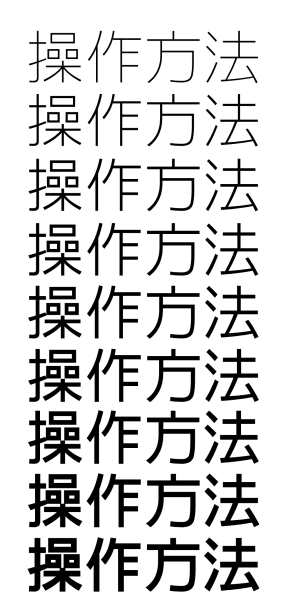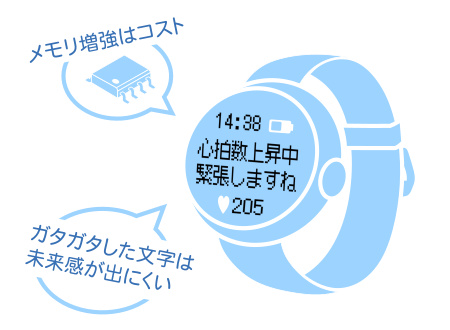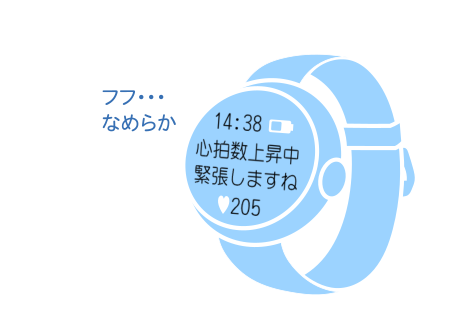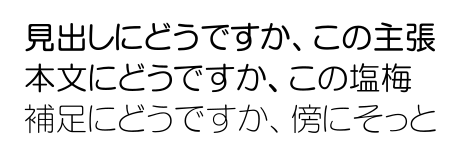
一言で表しますと、低容量なスケーラブルフォントです。みなさんはフォントって聞いて何を思い浮かべますか?今ご覧になっているこの文章もそうですね。スマホやPCで普段表示している文字といった感じでしょうか。
それらはおそらくTrueType Font(またはOpenType Font)です。
こんな文字もみたことありませんか?ビットマップフォントです。
そんなの知ってるよーという方、かなりお詳しいですね。でも、他にはもう種類がないと思っていませんか?
あるんです。
その中の1つが低容量スケーラブルフォントで、リコーではRT Fontと呼んでいます。
RT Fontならお望みの容量内に収まる可能性がありますし、文字もなめらかに表示できます。
TrueType Fontやビットマップフォントの場合、文字の太さや大きさが異なるとそれぞれフォントを買い足す必要があります。
しかし、RT Fontならその必要はありません。「ウェイト調整機能」や「縦横変倍機能」で十分表現できてしまうのです。
低容量化の仕組みや高速処理の秘密など、すごい所はまだまだあります。